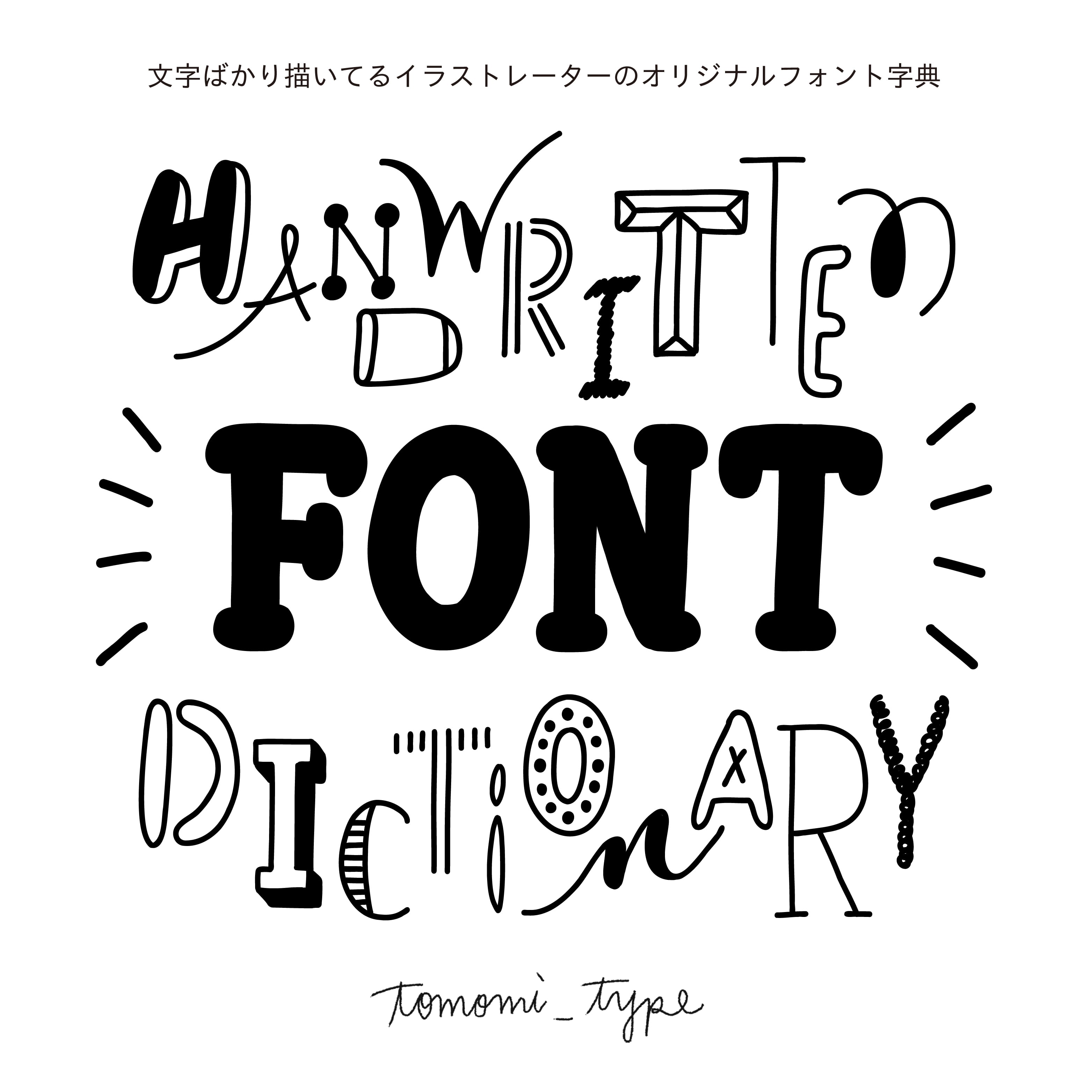
HANDWRITTEN FONT DICTIONARY 文字ばかり描いてるイラストレーターのオリジナルフォント字典
\トモミタイプオリジナルフォント字典ができました!/
文字ばかり描いてるイラストレーター、トモミタイプのオリジナルフォント字典。
既存のフォントを参考にせず、自分で思いついたフォントを絵のように描く私、トモミタイプ。
普段使いしやすいフォントから、思わず描いてみたくなるフォントや季節限定のフォントなど、133種類を一冊にまとめました。
アルファベット大文字・小文字・数字が掲載されています。(一部除く)
眺めるもよし、見様見真似で描いてみるもよし。使い方はあなた次第です!